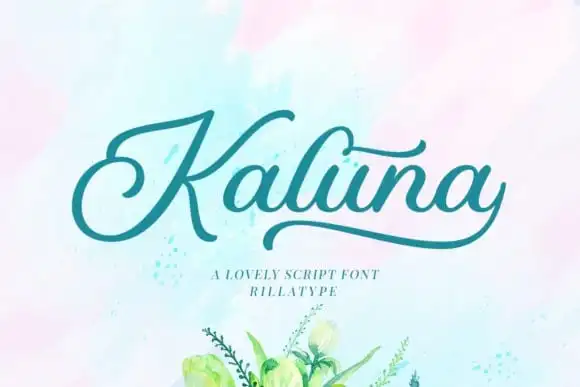
Kaluna Calligraphy Font – Download Grátis
A Kaluna Calligraphy Font é uma elegante tipografia script criada por Rillatype, apresentando um clima contemporâneo e moldes perfeitos inspirados na chamuscada classica do caligrafia eterna. Perfeitamente adaptável para o design de headlines, logotipos, roupas, convites, marcações, embalagens e anúncios, esta fonte oferece tudo que você precisa – desde as letras maiúsculas e minúsculas até os marcadores de pontuação e símbolos, e inclui setes alternativos, ligações e suporte para múltiplas línguas. Experimente personalizar o seu trabalho com caligrafia alternativa simplesmente adicionando a designação _1, _2 ou _3 à fonte principal. Por exemplo, Kaluna_1, Kaluna_2 ou Kaluna_3, e explore a variedade que cada uma oferece.